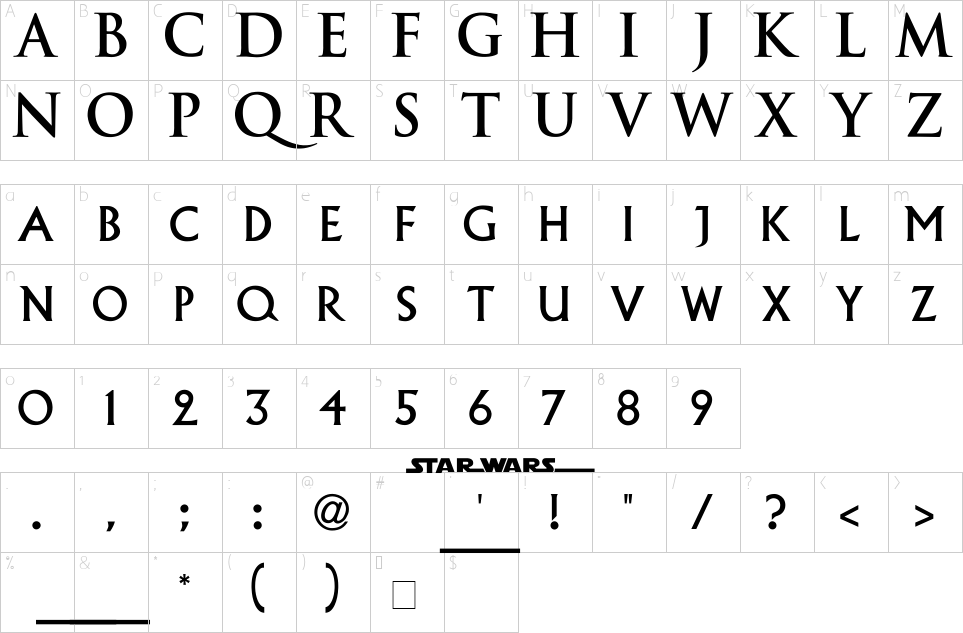
Descubra Episode 1, uma fonte grátis perfeita para sua próxima projeto visual no Windows ou Mac. Esta elegante e minimalista letra foi criada pelo talentoso designer Boba Fonts, disponível graças ao compromisso de fornecer recursos gratuitos que aprimoram o design digital. Episode 1 já recebeu mais de quarenta mil downloads desde seu lançamento, demonstrando sua popularidade e qualidade. Seja você um iniciante ou um profissional experiente, Episode 1 pode ser a fonte perfeita para seus projetos. Descubra agora e enriqueça suas criações com esta opção gratuita, sem comprometer a qualidade.